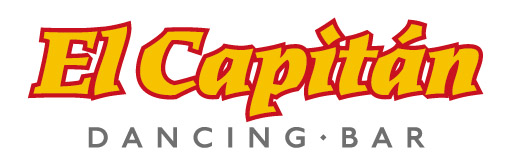
Schrift zu Thema 1650–1750
ich darf eine Schriftmarke für ein Lokal mit dem Titel El Capitan erstellen. Ich hätte dazu gerne eine Schrift, die für die Zeit zwischen 1650 und 1750 adäquat ist. Ich denke mal an eine Renaissance Antiqua, kann mir aber auch eine zu dieser Zeit passende Hand- oder Schreibschrift vorstellen.
Naja, 1650 ist doch eher noch Renaissance-Antiqua. Übergangsantiqua geht auch gut. Habe schon an die Mrs. Eaves gedacht. Sie sollte auf jeden Fall nicht zu sehr ins klassizistische rein gehen.
El Capitan und dann noch die genannte Epoche...
Da denke ich spontan an die Pracht und Macht Spaniens, deren Einfluß bis nach Böhmen und Mähren reichte. Wallenstein assoziiere ich damit, die Erbfolgekriege. Nie gab es eine Macht in Europa, die ungenierter ihre Macht zeigten. Als Schrift kommt mir da spontan eine Schreibschrift mit vielen - Ihr sagt so, oder? - Swashes in den Sinn. Eine Antiqua empfände ich als zu nüchtern.
Eine meiner Lieblingsschriften ist die eigenwillige, schwer zu bändigende Sirenne. Vielleicht etwas in diese Richtung?
»El Capitan« lässt mich natürlich an Südamerika denken. Schau dir mal die mexikanische Kimeratypefoundry von Gabriel Martinez Meave an. Pizarros Goldschätze sind dagegen Kinkerlitzchen. :D
Lagarto ist ein Prachtstück, meiner Meinung nach. Aber auch die Atzlan könnt ich mir vorstellen, als komplett anderes Gegenstück. Aber auch fast alle anderen von dort.
Kimeratypefoundry ist echt ein heißer Tipp. Kannte ich bisher noch nicht. Die Mexica kann ich mir auf den ersten Blick sehr gut für die Aufgabe vorstellen.
Ralf, dein Kennerley gefällt mir auch sehr gut. Bei dem Preis ja ein echtes Schnäppchen. Da der Tipp von dir kommt, nehme ich an, dass ich die Qualität nicht in Frage stellen muss!?
anbei die Lösung für die Schrift, nach der ich suchte. Mexica von Kimera ist’s geworden. Gefällt mir echt gut, die Schrift. Hatte auch Carta Marina und eine weitere Schrift von Kimera im Test.
Oh, da ist etwas verloren gegangen … Mich hat die Schriftwahl etwas verwundert, da doch »1650–1750« angepeilt wurde. Wie auch immer: Für ein »Dancing« (sagt man das bei euch noch?) sieht es prima aus.
Hab mir schon gedacht, dass du das so gemeint hast. Hast auch recht, dass das historisch nicht stimmt. Aber die Schrift hat Schmiss, einen etwas gebrochenen Charatker, passt in seiner Kantigkeit optimal zur kantigen Phonetik von El Capitán, vermittelt irgendwie spanisch/lateinamerikanisches Flair und passt hervorragend zu diesem Piraten, der von einer Kette als Logo oder Maskottchen oder so vorgegeben ist.